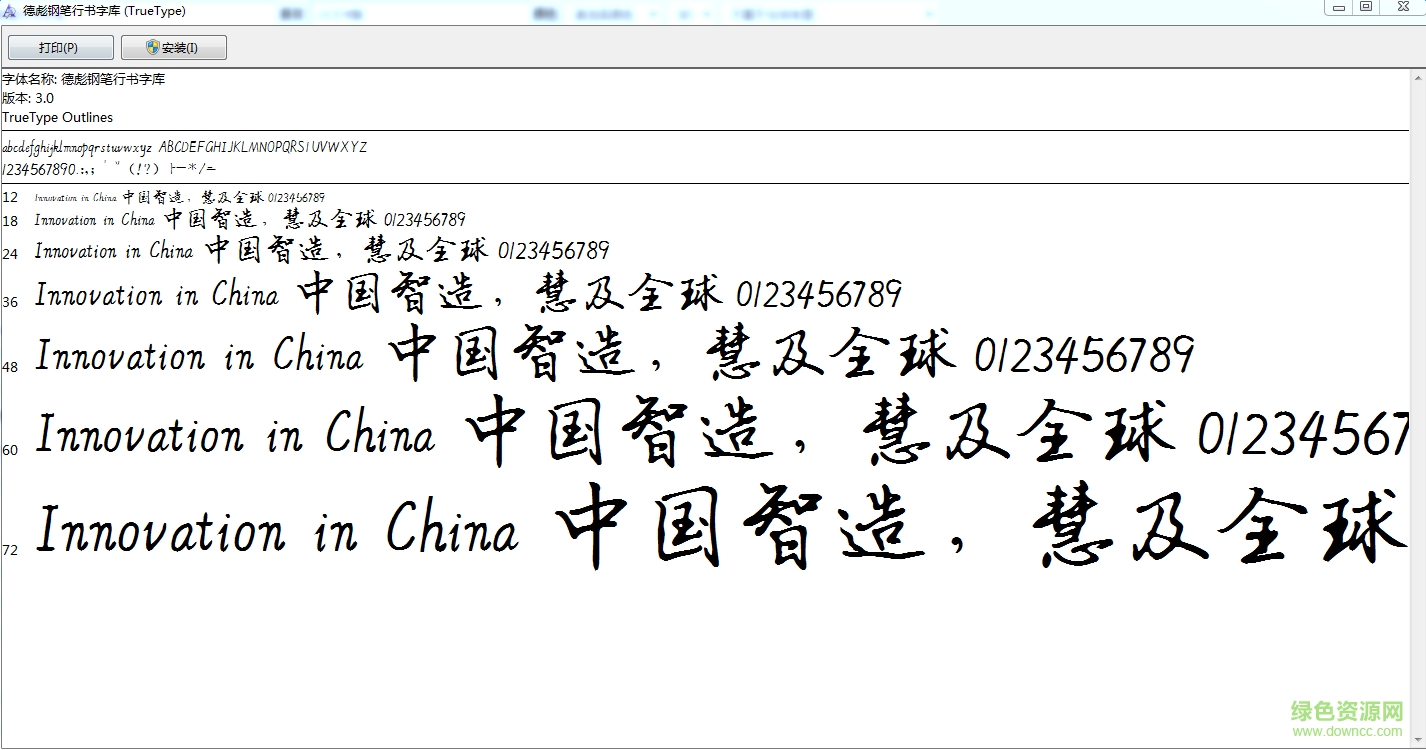
德彪鋼筆行書字庫字體3.0是一款ttf格式的硬筆行書字體,該字體筆墨飛揚,俊逸灑脫,不論是應(yīng)用于廣告還是印刷中都非常好看,喜歡的朋友快來綠色資源網(wǎng)下載吧!
行書是楷書的快寫,是楷書的流動。發(fā)現(xiàn)楷書與行書書寫時,點畫的寫法,用筆需遵循的準則,如中鋒,鋪毫,逆入平出,提按起主,藏鋒等都是一致的,只是行書書寫時比較舒展,流動。